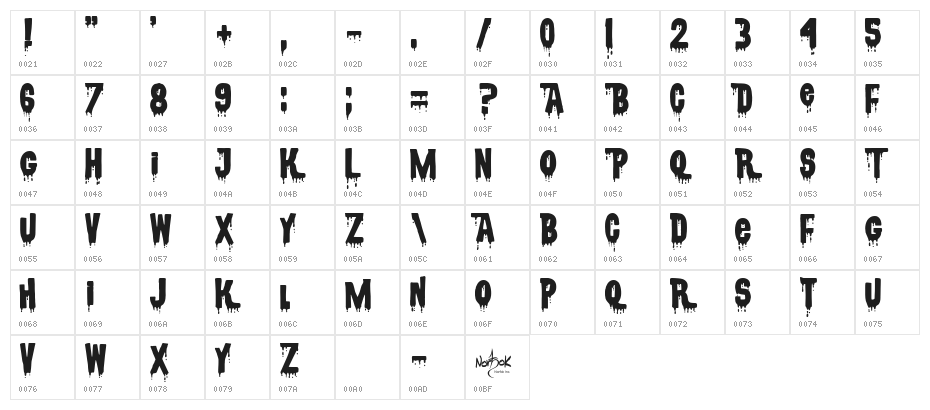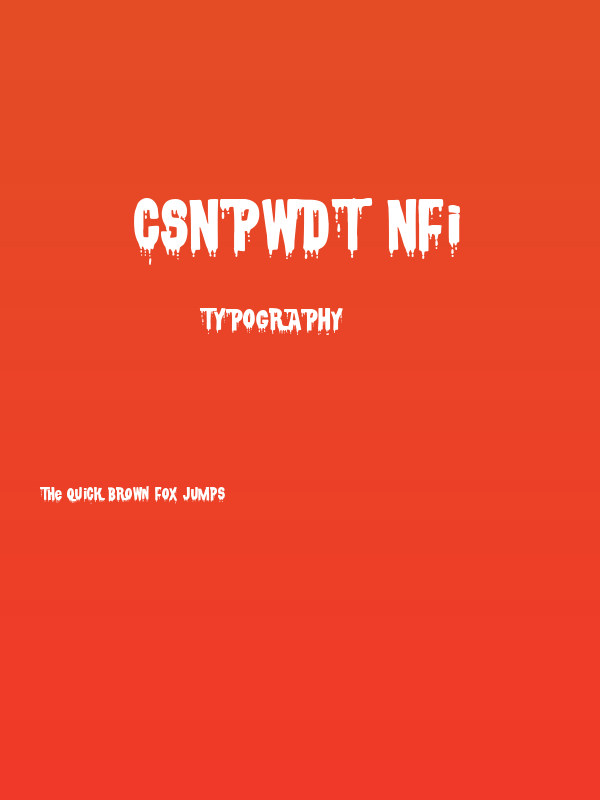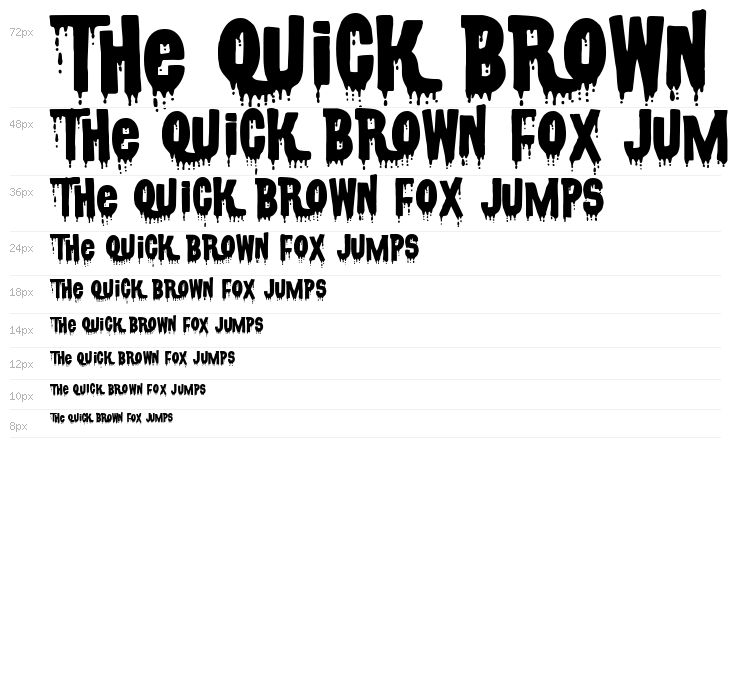
CSNPWDT NFI Font
✎ Drippy
| Categorie | Drippy |
| Progetti proposti | Ideal for Halloween-themed designs, horror movie posters, spooky event invitations, or any project requiring a dramatic and eerie typeface. |